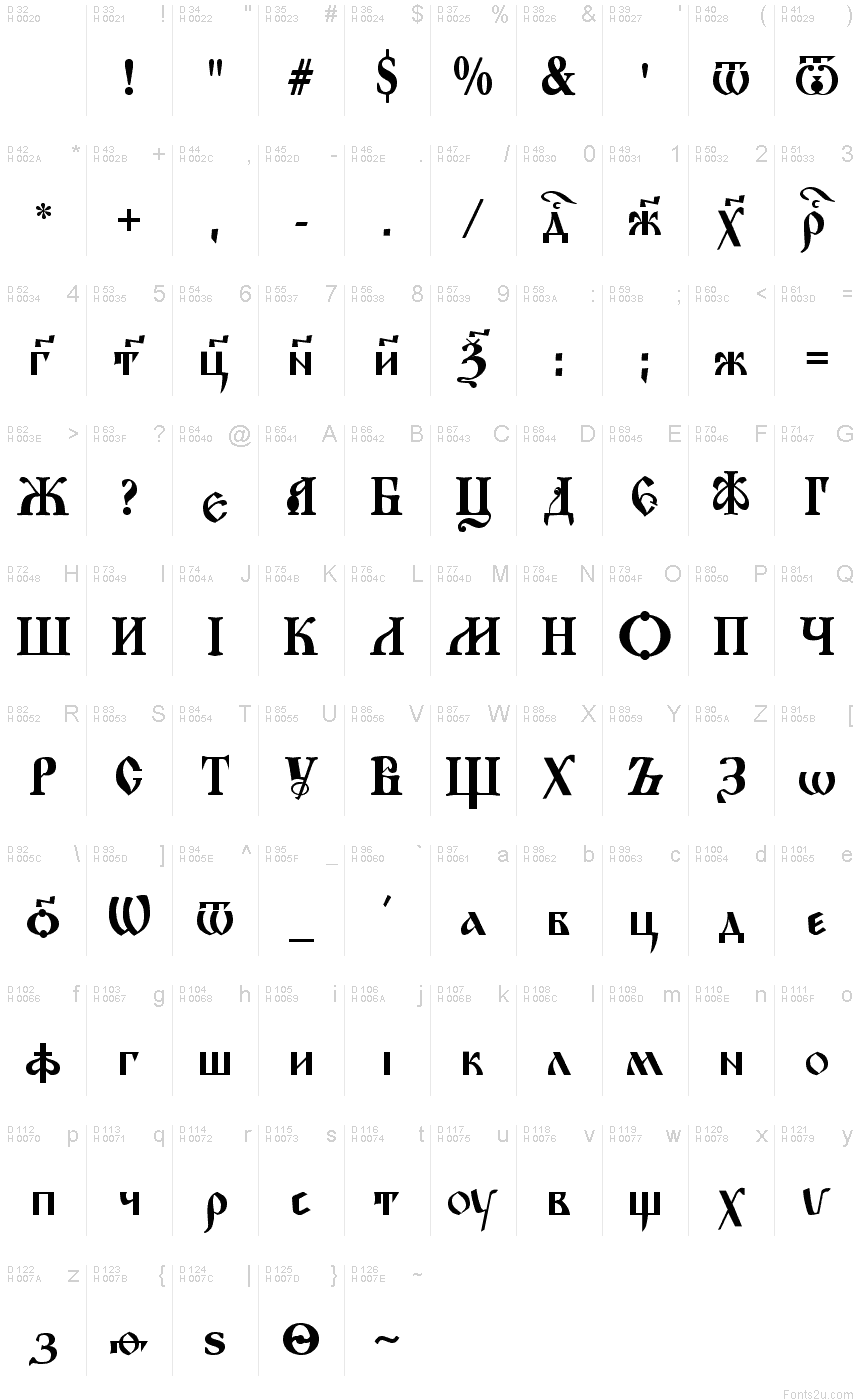
Evangelje Plain è un carattere cirillico blackletter gratuito di International Typeface Corporation, plasmato con il fascino dei manoscritti medievali e un’impronta più devozionale che severa. Le lettere combinano ampi tratti cesellati con giunzioni a goccia e tagli angolari, conferendo al carattere l'aspetto di una grafia liturgica trasposta in uno stile display compatto.
Si adatta perfettamente a copertine di libri, poster religiosi, branding per eventi storici, grafiche folk e titoli dove serve un carattere gratuito con un'atmosfera slava o ecclesiastica, senza risultare eccessivamente elaborato. Usalo per titoli brevi, iniziali o wordmark simili a monogrammi: le sue curve ad uncino e i tagli interni appuntiti donano anche alle composizioni più brevi un’inconfondibile impronta manoscritta.